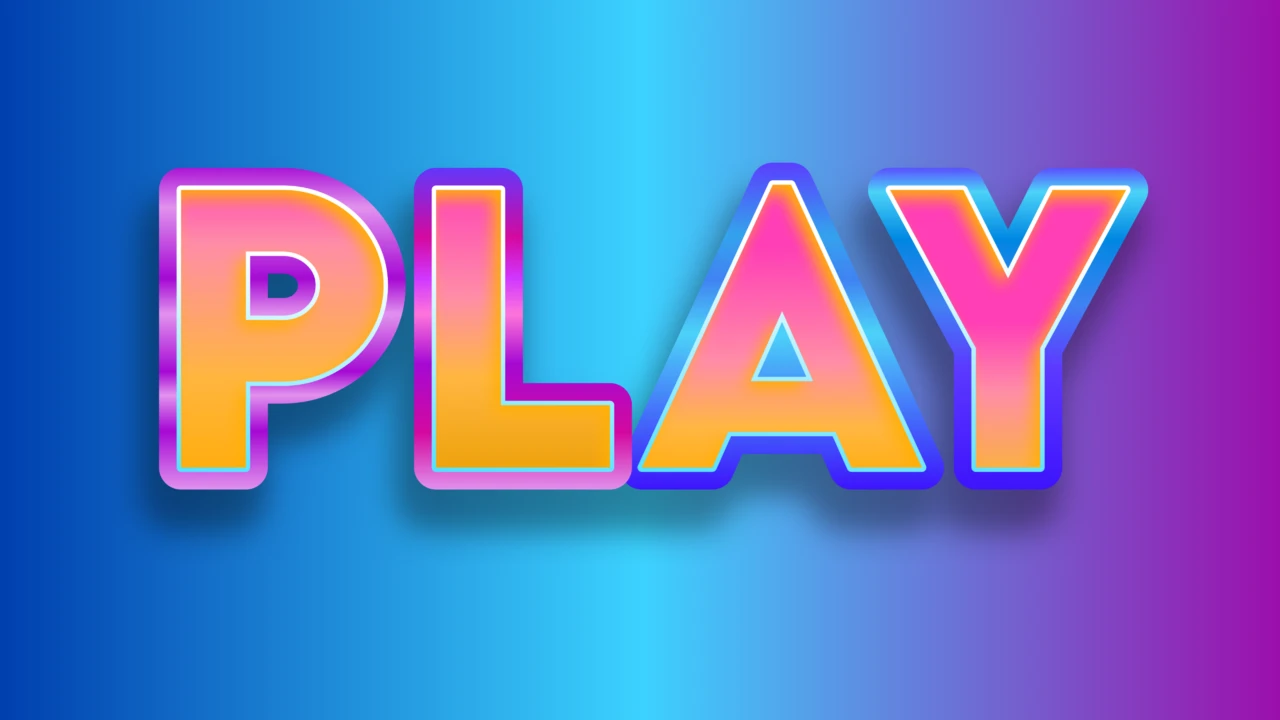
Glanzend retro neon verloop speels typografie-effect
Voeg een levendige, opvallende stijl toe aan je ontwerpen met dit glanzende, kleurrijke texteffect met gedurfde verlopen, gloeiende randen en een speelse retro sfeer die energie en plezier brengt in elk project.